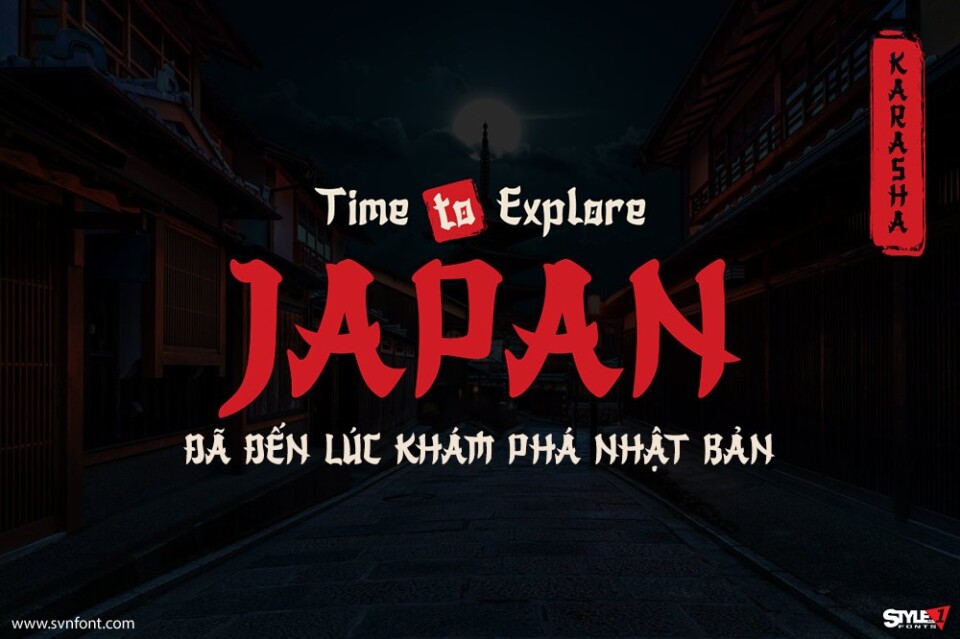
Font Việt hóa SVN Karasha – Nhật bản
Bạn đang tìm kiếm một bộ Font Miễn Phí độc đáo để làm nổi bật các thiết kế mang hơi hướng văn hóa truyền thống? Font Việt hóa SVN Karasha – Nhật bản chính là sự lựa chọn hoàn hảo dành cho bạn. Với những đường nét mô phỏng nét bút lông điêu luyện của nghệ thuật thư pháp Nhật Bản, bộ font này không chỉ mang lại vẻ đẹp cổ điển mà còn tạo nên dấu ấn mạnh mẽ cho mọi tác phẩm đồ họa.
Khám phá sức hút của Font Việt hóa SVN Karasha – Nhật bản
Bộ font này được thiết kế với các nét thanh đậm rõ rệt, mô phỏng chân thực kỹ thuật vẽ mực tàu trên giấy dó. Điều này giúp các ấn phẩm thiết kế trở nên có hồn và tinh tế hơn bao giờ hết.
Ứng dụng thực tế trong học tập và sáng tạo
• Thiết kế bìa sách, truyện tranh hoặc poster sự kiện văn hóa.
• Làm bài thuyết trình về lịch sử, nghệ thuật phương Đông.
• Sử dụng trong các dự án làm thiệp mời hoặc trang trí video.
Ưu điểm vượt trội khi sử dụng SVN Karasha
Điểm cộng lớn nhất của Font Việt hóa SVN Karasha – Nhật bản là tính tương thích cao với bảng mã Unicode. Người dùng có thể dễ dàng gõ tiếng Việt có dấu mà không lo lỗi hiển thị hay mất nét. Font chữ giữ được sự cân đối giữa các ký tự, giúp văn bản dù ngắn hay dài đều trông rất bắt mắt và chuyên nghiệp.
Lưu ý khi sử dụng font chữ
Vì đây là font dạng trang trí (display font), bạn nên sử dụng cho các tiêu đề lớn hoặc câu trích dẫn ngắn để đạt hiệu quả thẩm mỹ tốt nhất. Tránh dùng cho các đoạn văn bản quá dài để đảm bảo người xem không bị mỏi mắt.
Kết luận về bộ font độc đáo này